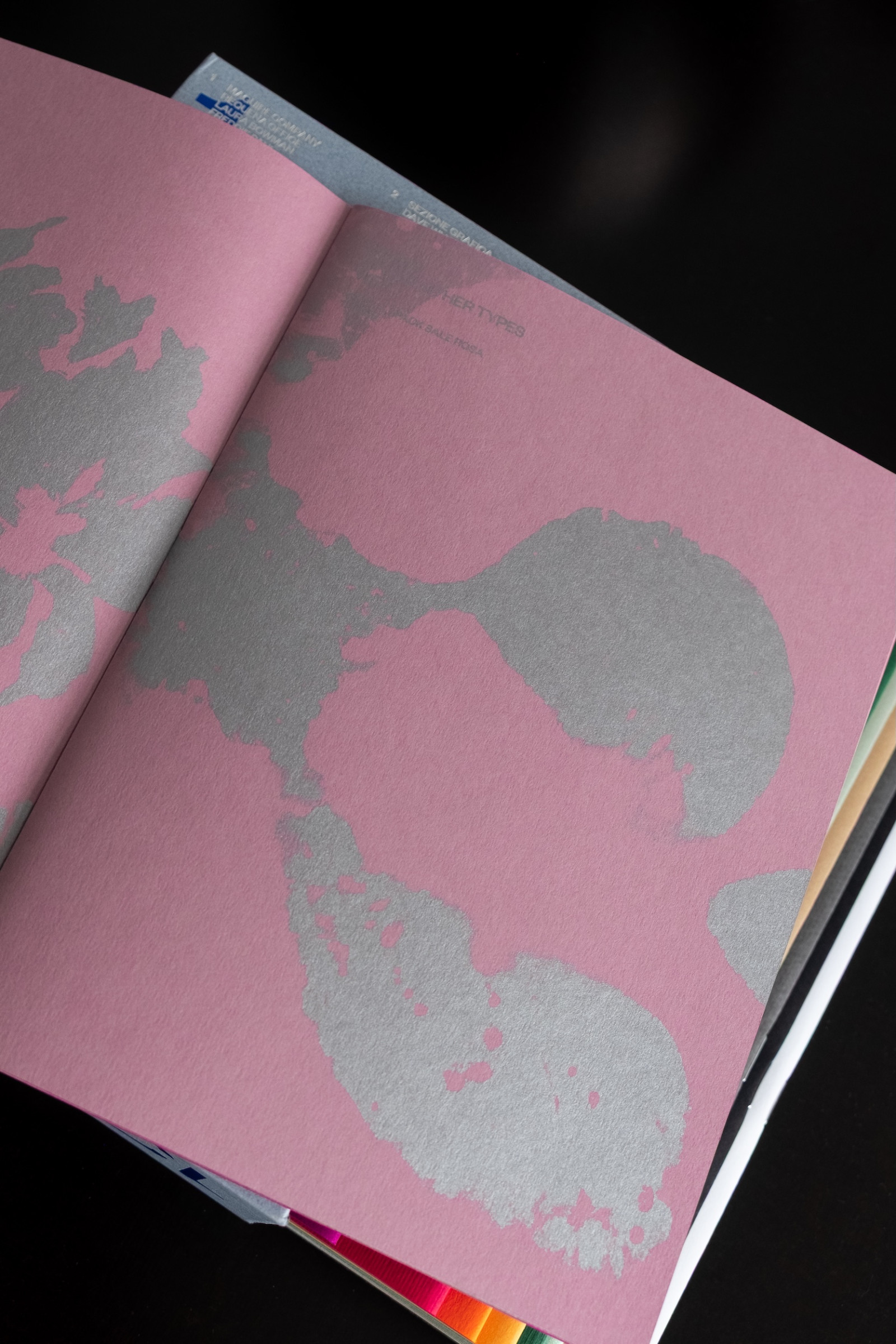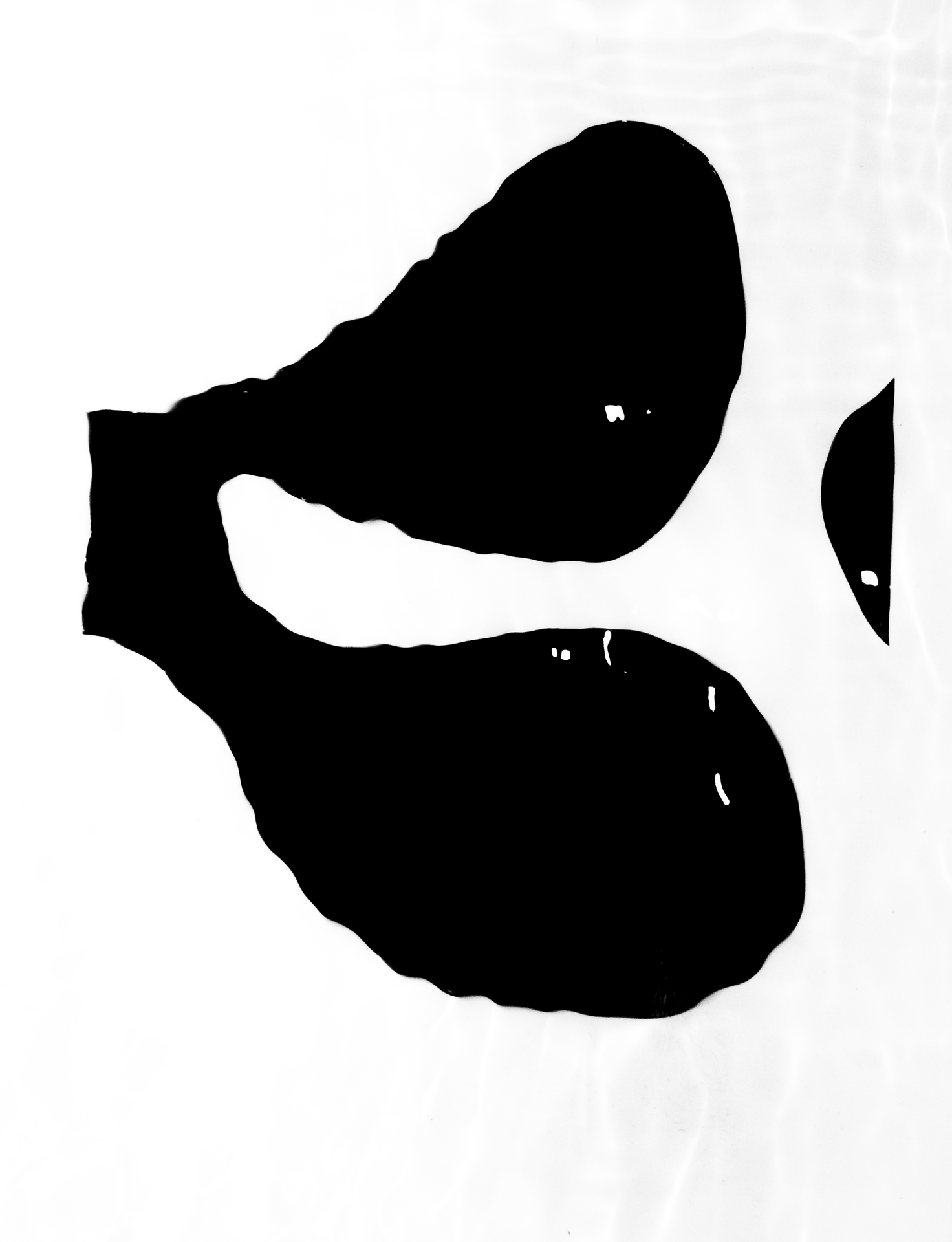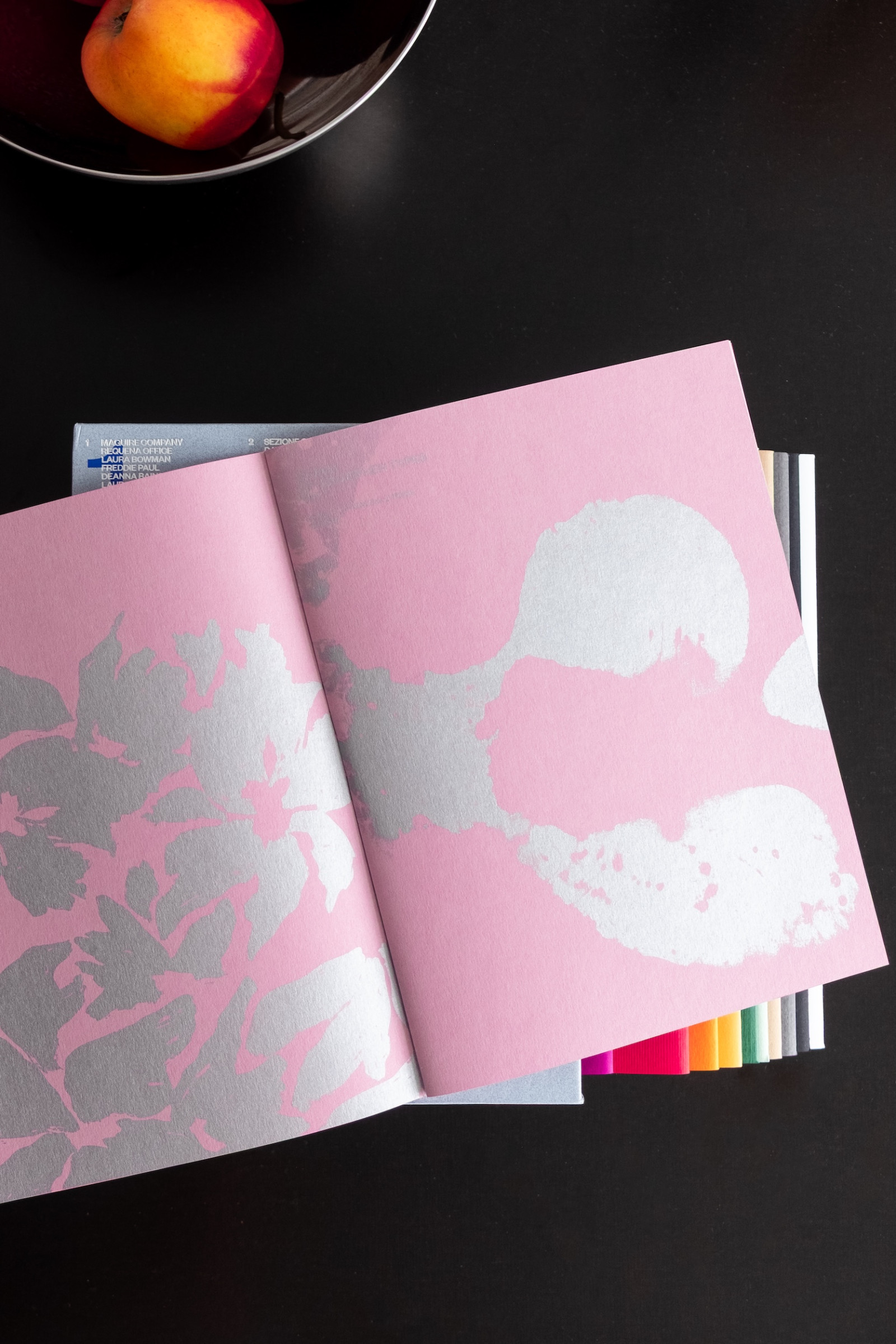
Fedrigoni 365 Kalender
Wir wurden eingeladen eine Seite des Fedrigoni 365 Kalenders 2026 zu gestalten.
Für den diesjährigen Fedrigoni 365 Kalender entstand unsere zugewiesene „3“ ganz analog: verschiedene gezeichnete Ziffern die per Hand gezeichnet wurden, haben wir wieder udn wieder, angepasst und verfeinert bis wir zu einem ansehnlichen Ergebnis gekommen sind. Die finale Version wurde digitalisiert, in Schwarz-Weiß gedruckt und ins Wasser gelegt. Das visuelle Ergebnis enstand ausschließlich durch die Bewegung der Wasseroberfläche, welche die angefertigte Form verzerrt und neu gestaltet.
Daraus enstand ein kurzer Moment zwischen Kontrolle und Zufall der als Ergebnis im Kalender zu sehen ist.